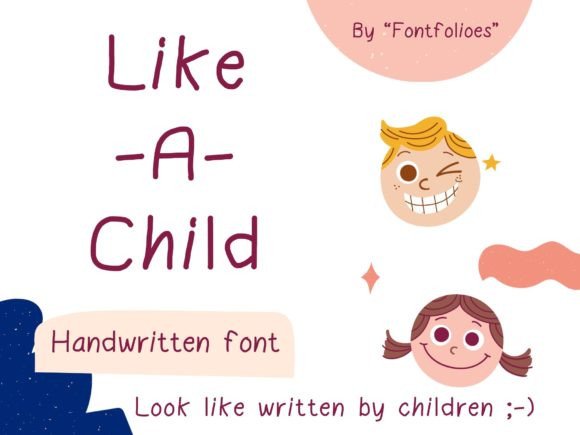
Like-a-child
Ulasan détaillée de la police « Like‑A‑Child » – Le charme de l’écriture enfantine
Vous cherchez une typographie qui transmet l’innocence et la créativité d’un premier gribouillage ? La police digitale Like‑A‑Child est exactement ce qu’il vous faut. Conçue pour reproduire les imperfections adorables d’une écriture d’enfant, elle apporte une touche ludique et authentique à tous vos projets graphiques.
Pourquoi choisir « Like‑A‑Child » ?
- Authenticité enfantine : chaque caractère possède des irrégularités naturelles – lignes légèrement décollées, angles doux et tailles variables – qui rappellent les premières tentatives d’écriture d’un petit.
- Versatilité créative : idéale pour les livres pour enfants, les supports éducatifs, les affiches de fêtes, les invitations, ou tout design nécessitant une note de légèreté et de joie.
- Impact émotionnel : la typographie suscite immédiatement le sourire, crée un lien affectif et rend votre contenu plus mémorable.
- Gamme complète de glyphes : lettres majuscules/minuscules, chiffres, ponctuation et symboles spéciaux
Applications idéales
- Matériel pédagogique – fiches d’activités, manuels scolaires, affiches de classe
- Livres illustrés pour enfants – couvertures, chapitres, notes de fin
- Communication marketing – flyers, newsletters, posts sur les réseaux sociaux
- Projets personnels – cartes de vœux, journaux créatifs, scrapbooking
En résumé, Like‑A‑Child est la police parfaite pour injecter une dose de fraîcheur et de spontanéité dans vos créations. Son style unique, à la fois « brut » et « charmant », fait de chaque texte un petit chef‑d’œuvre plein de personnalité. Téléchargez‑la dès maintenant et laissez votre design parler le langage du cœur d’un enfant.